دانلود Retro Style Font Bundle 20 فونت انگلیسی با استایل رترو
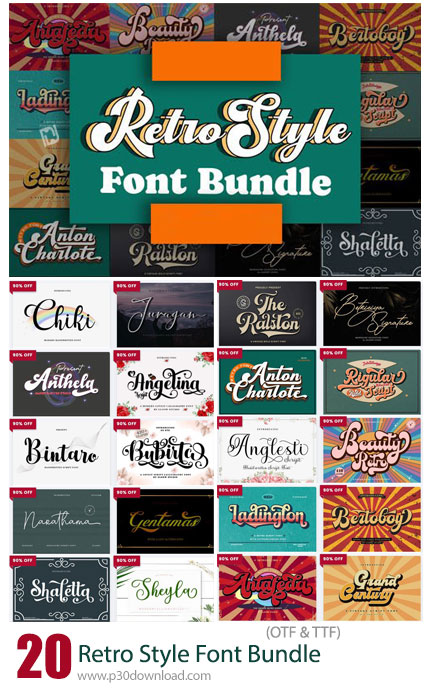
در این بخش شاهد 20 فونت انگلیسی با استایل رترو می باشید که با فرمت های OTF و TTF بر روی سایت برای دانلود قرار گرفته است. بسته فونت سبک رترو مجموعهای منحصر به فرد از فونتهایی است که الهام گرفته از سبکهای طراحی دهههای گذشته هستند. این بسته شامل چندین فونت با ظاهری قدیمی و نوستالژیک است که میتواند به پروژههای طراحی شما جذابیت و اصالت ویژهای ببخشد. بسته فونت سبک رترو شامل مجموعهای از فونتهای متنوع با طراحیهای مختلف است که هر کدام بهطور منحصر به فردی نمایانگر سبکهای طراحی دهههای مختلف، مانند دهههای 50، 60، 70 و 80 میلادی هستند. تمامی فونتهای این بسته با دقت و جزئیات بالا طراحی شدهاند تا بهترین کیفیت را در نمایش و چاپ ارائه دهند. این فونتها به خوبی با نرمافزارهای مختلف طراحی و ویرایش گرافیکی سازگار هستند. با استفاده از بسته فونت سبک رترو میتوانید به راحتی و به سرعت فونتهای منحصر به فرد و نوستالژیک را در پروژههای طراحی خود به کار ببرید و به آنها جذابیت و اصالت ویژهای ببخشید.